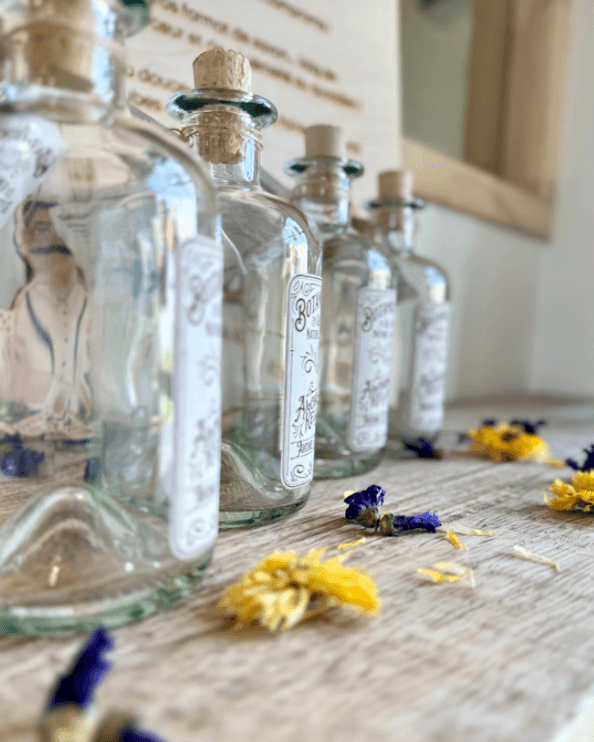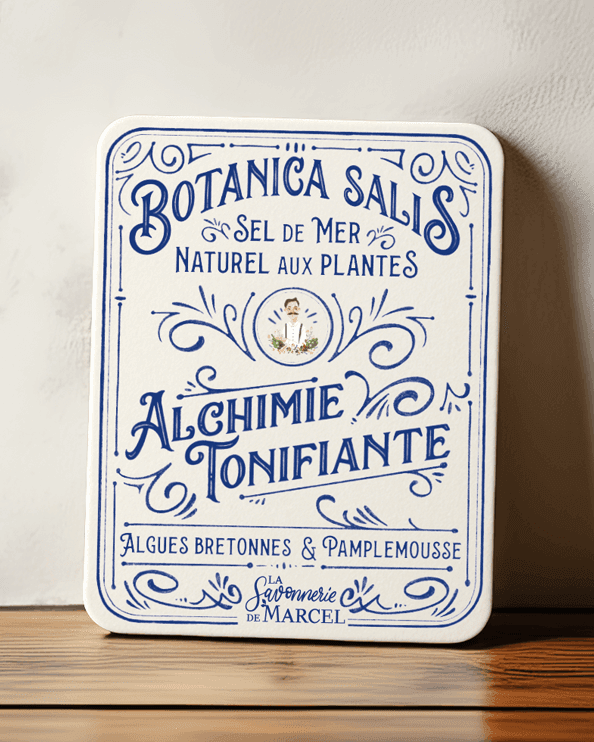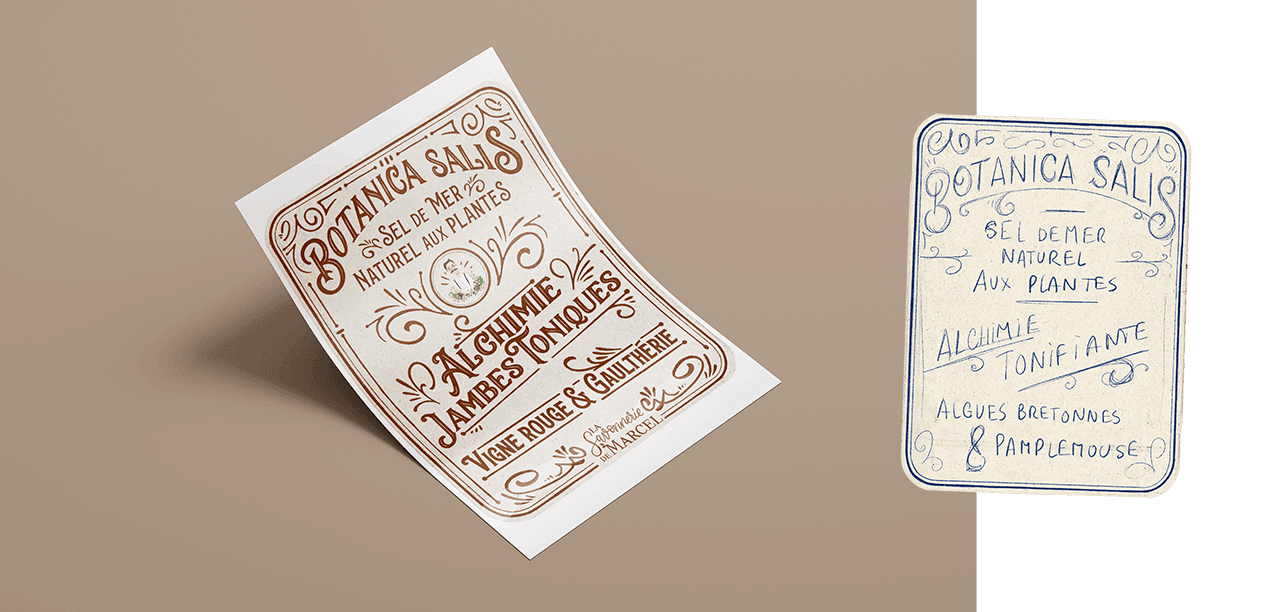
La Savonnerie de Marcel a créé une gamme de sels de bain naturels, conçue en collaboration avec des producteurs locaux. Un produit de grande qualité, bio et 100 % fabriqué sur place.
Le client souhaitait un style inspiré des codes pharmaceutiques d’antan et des parfumeries d’époque, avec une typographie élégante et un papier texturé rappelant les supports anciens.
Le choix s’est porté sur une étiquette raffinée, jouant sur des teintes naturelles et une texture authentique. Le tout habillant une bouteille d’antan, scellée du sigle de la savonnerie en cire.
Ce travail d’identité souligne la force de la marque : ancrée dans la tradition et privilégiant la qualité, le sain et le local.